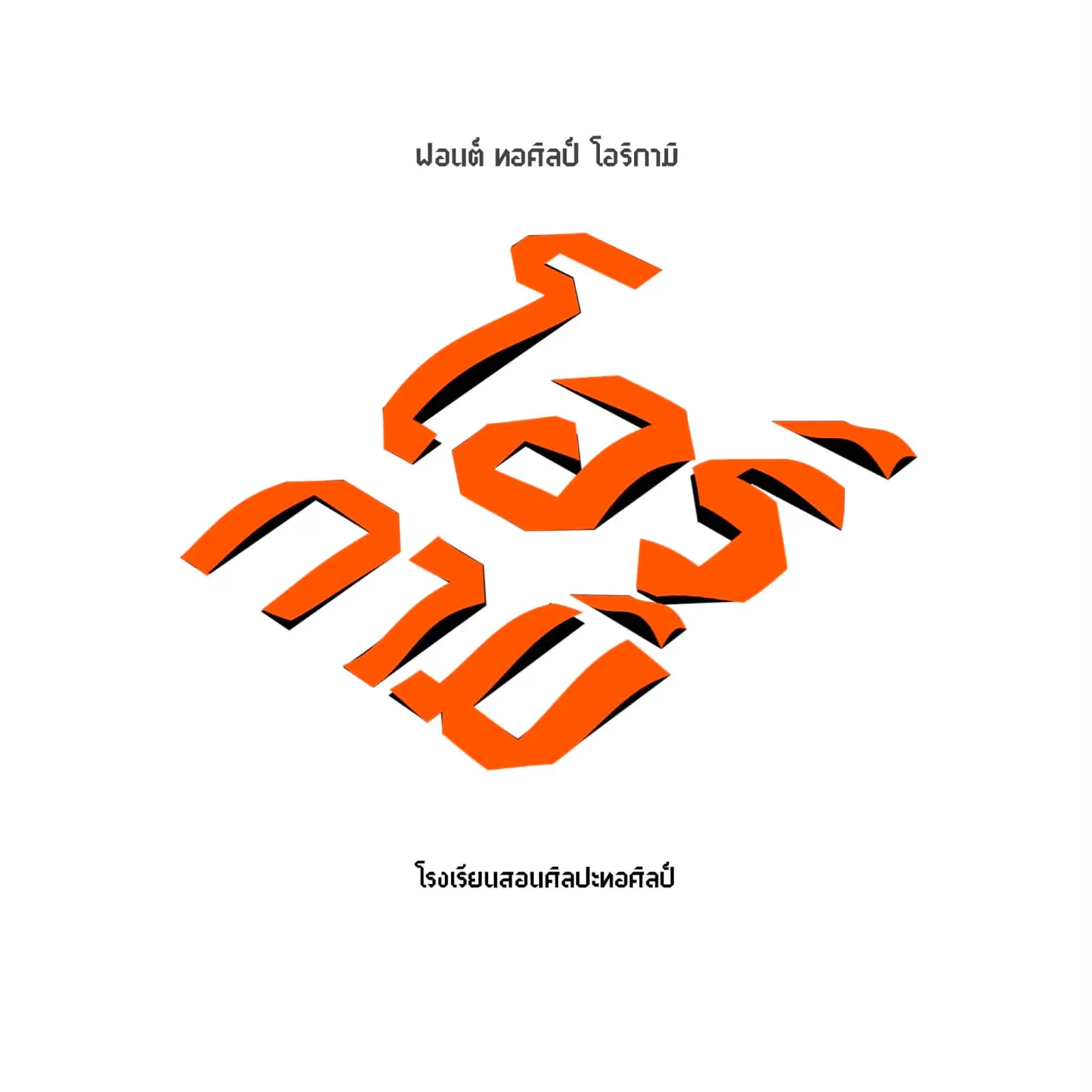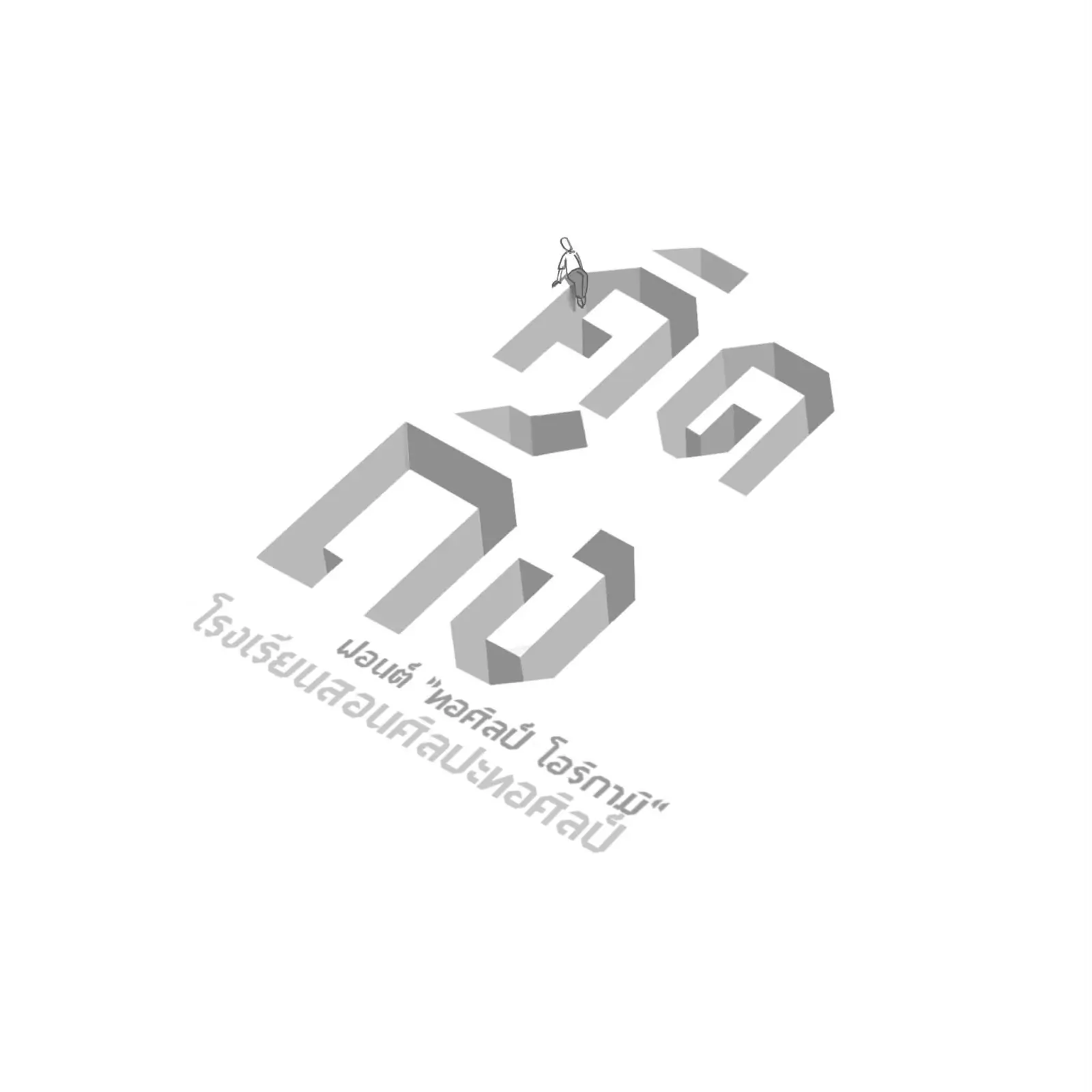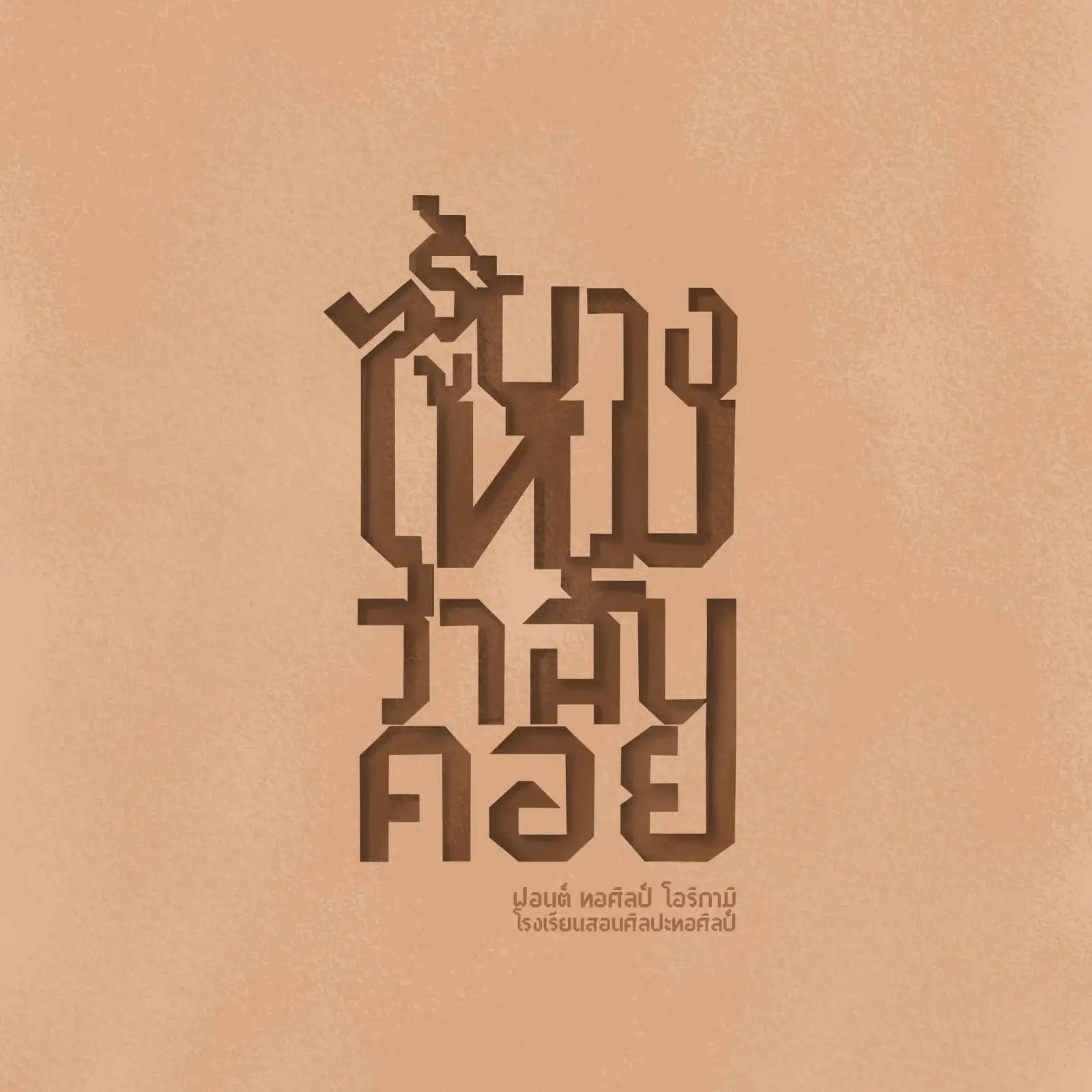
ฟอนต์ “ทอศิลป์ โอริกามิ” – แรงบันดาลใจในการออกแบบฟอนต์นี้ มาจากการเอากระดาษมาพับไปมาเป็นตัวหนังสือของลูกศิษย์ เห็นแล้วเกิดไอเดียให้นำมาต่อยอดเป็นฟอนต์
ทอศิลป์ โอริกามิ (Torsilp Origami)